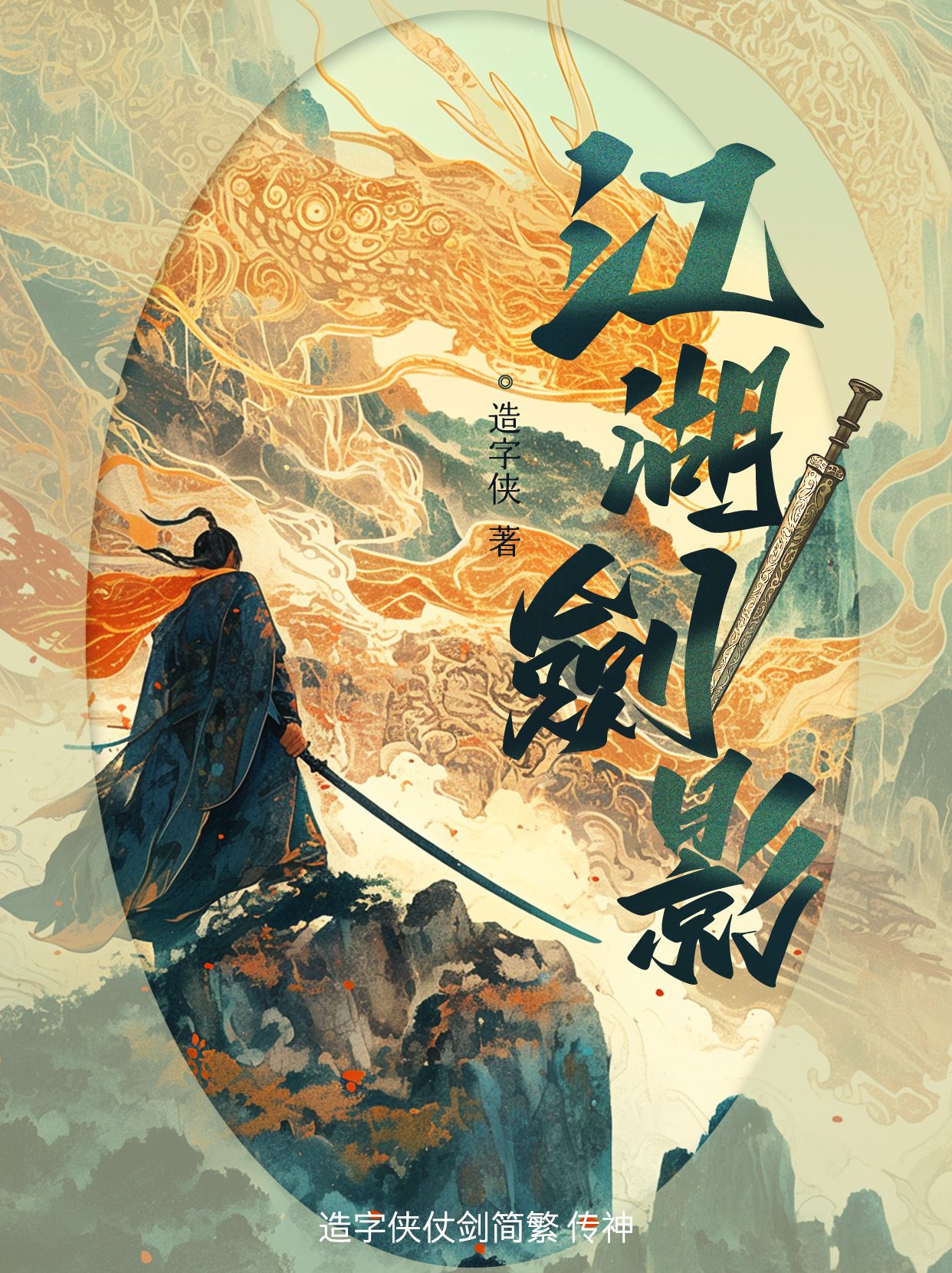
四款小红书字体推荐:用字形点燃视觉爆点
在小红书「颜值即正义」的内容生态中,封面与视频的字体选择直接影响点击率与互动量。从浪漫优雅到热血江湖,从摩登都市到治愈萌系,本文精选四款风格鲜明的商业字体,助你精准传递内容调性,打造吸睛视觉符号。
1. 造字侠郝刚快乐简 微黑
112度倾斜的斜体设计,让这款字体自带「巴黎左岸」的慵懒气质。西文斜体的优雅弧度与隶书「蚕头燕尾」的古典韵味碰撞出奇妙火花,既保留汉字的骨力,又增添流动的韵律感。在美妆教程封面、旅行Vlog标题或时尚穿搭视频中,其轻盈跃动的字形能瞬间提升画面精致度,尤其适合「氛围感」内容——比如搭配莫兰迪色系背景,传递法式轻奢或东方雅韵的混搭美学。
2. 造字侠仗剑简繁 传神
以「仗剑天涯」为魂的书法字体,笔画如刀剑出鞘般锋利,折提钩画高度折叠,力透纸背的笔锋自带江湖侠气。在运动健身教程封面、国风汉服视频标题或游戏解说字幕中,其苍劲有力的字形能瞬间点燃观众肾上腺素。例如搭配水墨风背景或武侠风BGM,轻松营造「十步杀一人,千里不留行」的热血氛围,尤其适合需要传递力量感或文化底蕴的内容。
3. 励字造梦简 特粗
不对称的「左倾右直」结构,让这款字体如摩天大楼般充满压迫感与未来感。夸张的透视效果模拟仰视视角,棱角分明的直线切割出几何张力,在科技感视频封面、职场干货标题或城市探索类Vlog中,能瞬间强化「Z世代」的锐气与野心。搭配霓虹灯色系或金属质感背景,其冷峻有力的形态能精准传递「打破常规,向上生长」的青春宣言。
4. MyFont郑明瑾卡通简
圆润如棉花糖的弧线与柔和转角,让每个字都像咧嘴微笑的卡通角色。这款字体自带「童真滤镜」,在萌宠日常视频、母婴好物推荐或亲子活动封面中,能瞬间消解画面的尖锐感,传递温暖治愈的能量。例如搭配马卡龙色系或手绘插画背景,其无攻击性的视觉语言能迅速拉近与观众的距离,尤其适合需要传递「柔软」与「陪伴」的治愈系内容。
从浪漫斜体到江湖侠气,从建筑透视到萌系治愈,这四款字体以精准的设计语言回应着小红书内容的多元需求。它们不仅是文字的容器,更是情绪的放大器——在碎片化的信息流中,选择与内容同频的字体,往往能让封面「一眼入魂」,让视频「帧帧动人」。